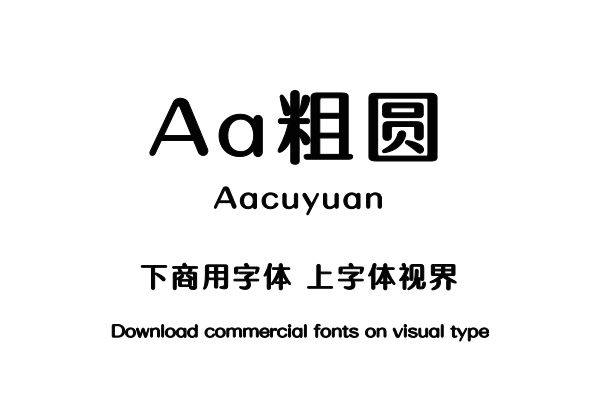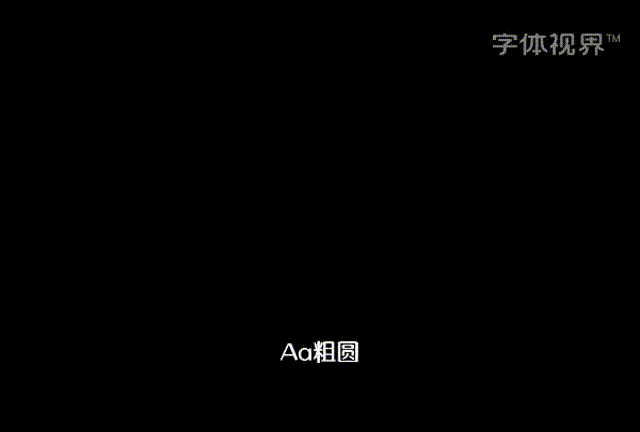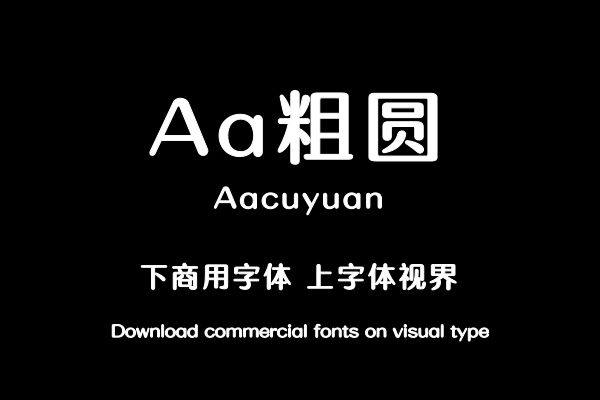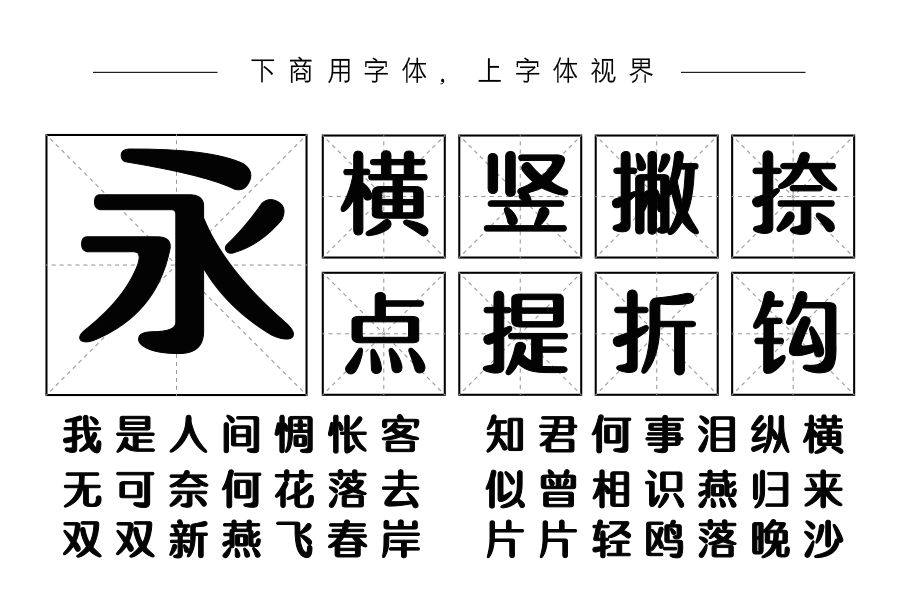
Aa粗圆结构饱满大方,笔画圆头,粗细对比明显,撇捺舒展且柔和,整体美观柔和,适用性强。可作为标题字使用,适用于书籍、影视、广告等使用场景。购买须知:“下载服务费”与“字体VIP”所获得字体 仅用于个人非商用, 商用请联系付费授权。本字体为电脑用字,手机没有root权限不支持直接手机换字(手机如何root,请自行百度搜索教程)。购买前请先 了解清楚后再付款 ,字体为虚拟产品无法回收 一旦购买不支持退款。